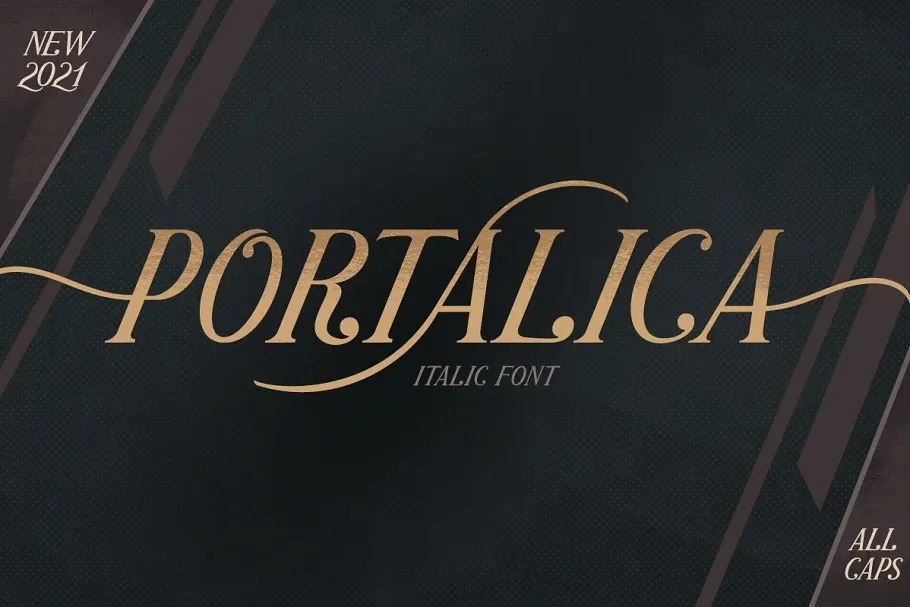
Portalica Font – Fonte Grátis
Portalica Font
O Portalica Font é uma elegante fónt serif que captura a essência do neoclasicismo com alta contraste e estilo único. Seu design cool e singular permite uma aparência vibrante para letras e logotipos, dando-lhes um toque de originalidade. Com suas ondulações finas e bem definidas, o Portalica se destaca ao combinar a clareza e organização típicas das fóntes serif com um toque de movimento e criatividade nas bordas dos caracteres. Perfeito para designers buscando adicionar uma camada extra de interessamento em seus trabalhos, este font é certamente uma escolha inovadora que se tornará o centro da atenção nos seus projetos visuais.